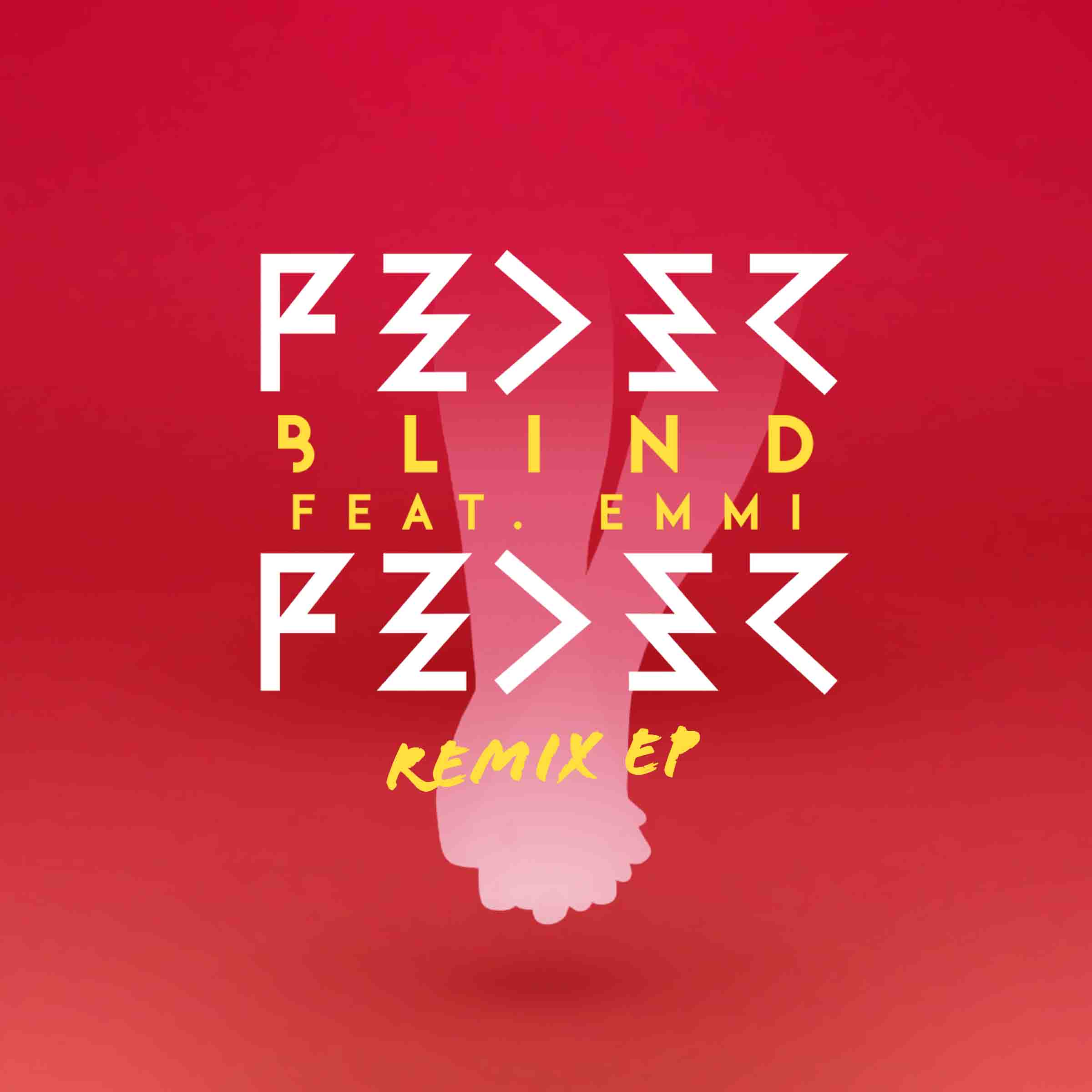
Welche Font / Schriftart ist das? (Feder DJ)
Das sieht mir nicht nach einer Schriftart aus, sondern wurde eher aus dem gelben Font entwickelt.
Google sagt: Die kryptischen Zeichen bedeuten das Wort „Feder“. *kopfschüttel* In den Seiten mit den experimentellen Grotesk wurde wohl noch sehr untertrieben, es geht wilder und noch weiter an den Konventionen der Kommunikation vorbei. Das ist ein sehr interessantes Beispiel für solche [w}irren Schriften und regt den Einen oder die Andere bestimmt zu weiteren Gedanken an.
*kopfschüttel* In den Seiten mit den experimentellen Grotesk wurde wohl noch sehr untertrieben, es geht wilder und noch weiter an den Konventionen der Kommunikation vorbei.
Hm, evtl. ist es eine condensed Version der "acute-solid"?
Diese experimentellen Grotesk sind entweder unlesbar oder sehen scheiße aus oder sind gar beides. Und wenn sie das ausnahmsweise nicht tun, dann sehen die so was von 1926 aus ...
Ich würde es etwas wohlwollender ausdrücken wollen: sie siehen oft wie aus einer Low budget Science fiction Produktion aus ;-)